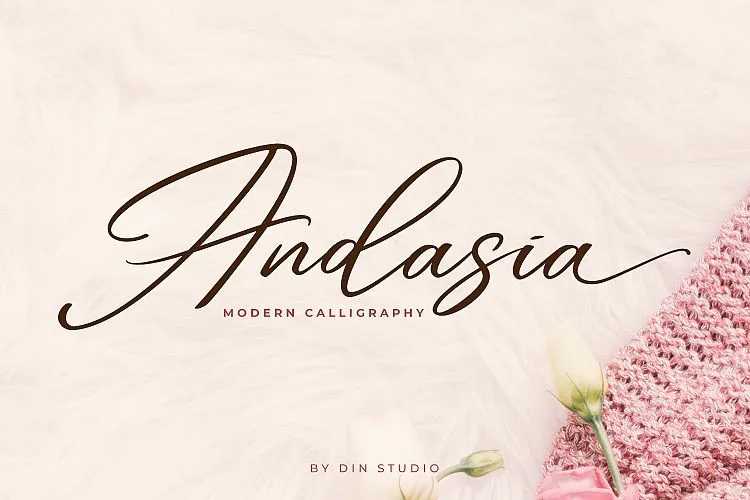
Andasia Script Font – Fonte Grátis
Andasia Script Font
Andasia Script é uma elegante tipografia moderna com estilo de escrita natural e autêntica. Inspirada na calligrafia contemporânea, essa fonte traz um toque sofisticado para eventos formais como casamentos, marcas de identidade visual (branding), logotipos e mensagens inspiradoras. Com sua textura única e sua harmonia perfeita entre a modernidade e o estilo livre da escrita manual, Andasia Script é ideal para aqueles que buscam uma tipografia sofisticada e versátil para seus projetos gráficos. Não importa qual tipo de projeto você está planejando, essa fonte oferece um toque único e profissional, tornando qualquer trabalho mais belo e criativo.